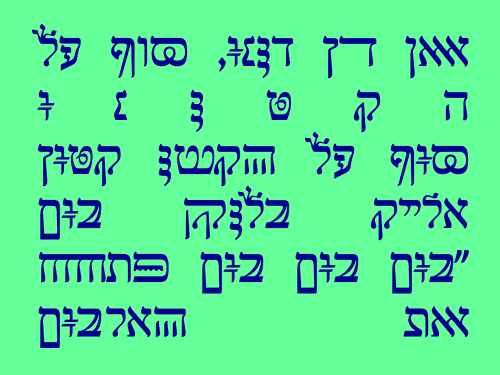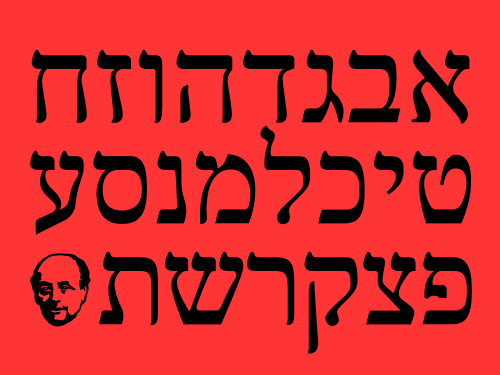
פרק חדש בסיפורו של הפונט העברי שעיצב במידה רבה את השפה העברית ב־110 השנים האחרונות.
פרנק־רי עוצב מתוך אהבה עצומה לאות העברית, ובמטרה להקפיץ את הגדוּלה של ״פרנק־ריהל״ למאה העשרים ואחת, מבלי לאבד את הקסם הקלאסי שלו.
בשנת 1910 רפאל פרנק עיצב 27 אותיות קלאסיות שמסמלות היום יותר מכל את אתוס תחיית השפה העברית. היום בעידן הדיגיטלי של טשטוש זהויות, יש לנו צורך, יותר מתמיד, לזהוּת ויזואלית עברית.
הוא כולל נִקּוּד מֻקְפָּד וְתִקְנִי, טַ֟ע֤֙מֵי֧־הַ֒מִּ֖קְ֓רָא֣֗ לעימוד טקסטים מקראיים, OpenType™ Features לשליטה בדקויות ובניואנסים הטיפוגרפיים ומערך תואם של אותיות באנגלית ותמיכה ב־229 שפות לטיניות.
פרנק־רי כולל מערך מלא של אותיות נטויות ייחודיות המיועדות להדגשה עדינה של האותיות ה״רגילות״. בנוסף, הן משמשות כפונט עצמאי – לכותרות ולטקסטים קצרים.
היום, בעידן הדיגיטלי, אנחנו זקוקים יותר מתמיד לזהוּת ויזואלית עברית, כזאת שהיא שורשית באותה המידה שהיא עדכנית. פונט פרנק־רי עוצב מתוך אהבה עצומה לאות העברית, ובמטרה להקפיץ את הגדוּלה של ״פרנק־ריהל״ למאה העשרים ואחת, מבלי לאבד את הקסם הקלאסי שלו. פרנק־רי הוא פונט סוּפר מקצועי, הכולל: גרסא נטויה, נִקּוּד מֻקְפָּד וְתִקְנִי, טעמי־המקרא, OpenType™ Features ותמיכה ב־229 שפות לטיניות. במבט ראשון פרנק־רי ירגיש מאד מוכר, אבל העין המיומנת תבחין בפרטים הקטנים ובניואנסים. הוא קריא מאד ומתאים גם לדפוס וגם לדיגיטל, בטקסט־רץ הוא ״שקוף״ וכפונט כותרות הוא דורש את הבמה. הוא פונט יומיומי, עכשווי ו... סוּפר שימושי.
Today, in the digital age, we need to conserve the Hebrew’s visual identity more than ever, one that will be connected to its roots in as much as it will be state of the art. FrankRe was designed with a great love for the Hebrew alphabet, with the aim of moving the greatness of "FrankRuehl" into the 21st century, without losing its classic charm. At first FrankRe will feel very familiar, but the skilled eye will notice the small details and nuances. It is very readable and suitable for both print and digital texts; in runner text it is "transparent" and as a headline it takes center stage. It is an every day, contemporary and extremely useful font.
כשרפאל פרנק עיצב את הפונט הקלאסי ״פרנק־ריהל״ לפני 110 שנים, הוא הגדיר במידה רבה את העברית המתחדשת הכתובה. הוא יצר לנו גשר בין האות העברית הקדומה והדתית, לבין העברית הלאומית, העשירה והתוססת. כזאת שמייצרת ספרות יפה, כותרות בעיתונים ושלטי חוצות.
היום, בעידן הדיגיטלי, אנחנו זקוקים יותר מתמיד לזהוּת ויזואלית עברית, כזאת שהיא שורשית באותה המידה שהיא עדכנית. פונט פרנק־רי עוצב מתוך אהבה עצומה לאות העברית, ובמטרה להקפיץ את הגדוּלה של ״פרנק־ריהל״ למאה העשרים ואחת, מבלי לאבד את הקסם הקלאסי שלו.
פרנק־רי כולל מערך תואם אותיות נטויות ייחודיות המשמשות להדגשה עדינה של האותיות ה״רגילות״ וכפונט עצמאי – לכותרות ולטקסטים קצרים.
פרנק־רי הוא פונט סוּפר מקצועי, הכולל: נִקּוּד מֻקְפָּד וְתִקְנִי, טעמי־המקרא לעימוד טקסטים מקראיים, OpenType™ Features לשליטה בדקויות ובניואנסים הטיפוגרפיים ומערך תואם של אותיות באנגלית ותמיכה ב־229 שפות לטיניות.
במבט ראשון פרנק־רי ירגיש מאד מוּכר, אבל העין המיומנת תבחין בפרטים הקטנים ובניואנסים. הוא קריא מאד ומתאים גם לדפוס וגם לדיגיטל, בטקסט־רץ הוא ״שקוף״ וכפונט כותרות הוא דורש את הבמה.
רגיל ורגיל־נטוירק לטקסט־רץ. בדפוס: 6 pt ומעלה; בדיגיטל: 20 px ומעלה.
בינוני ובינוני־נטוי לטקסטים בכל הגדלים. בדפוס: 7 pt ומעלה; בדיגיטל: 20 px ומעלה.
בולד ובולד־נטוילכותרות מפילות לסתות ולהדגשה של מספר מילים בטקסט־רץ.